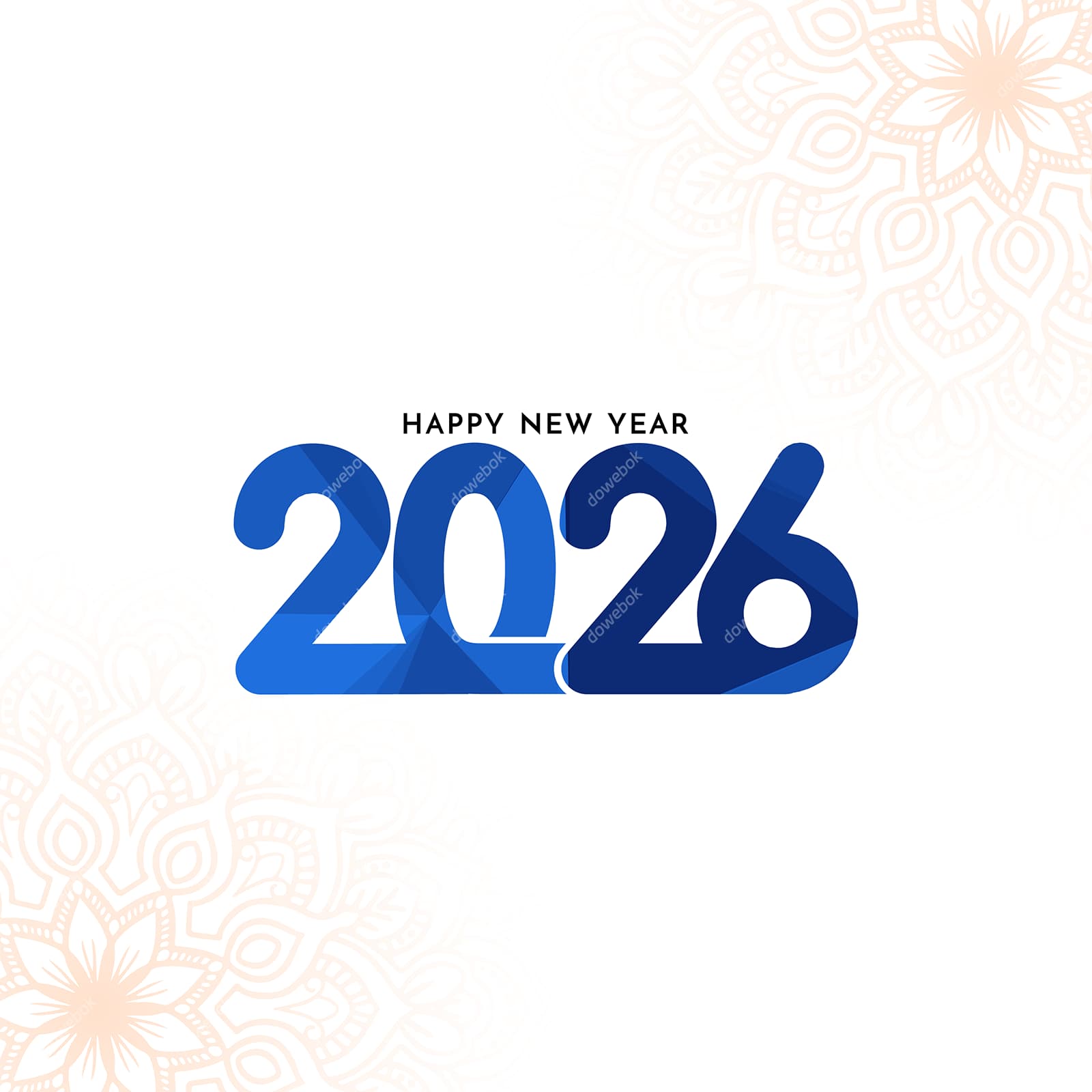
这是一款蓝色渐变数字设计的 2026 新年快乐矢量素材,白底衬着浅米色曼陀罗花纹,风格清新雅致。画面中央是蓝渐变几何拼接的 “2026” 字体,质感现代简洁,上方配黑色 “Happy New Year” 英文。整体设计以简约配色和装饰元素,既突出新年主题,又通过几何造型传递出轻盈的现代感,适合作为新年贺卡类视觉素材。